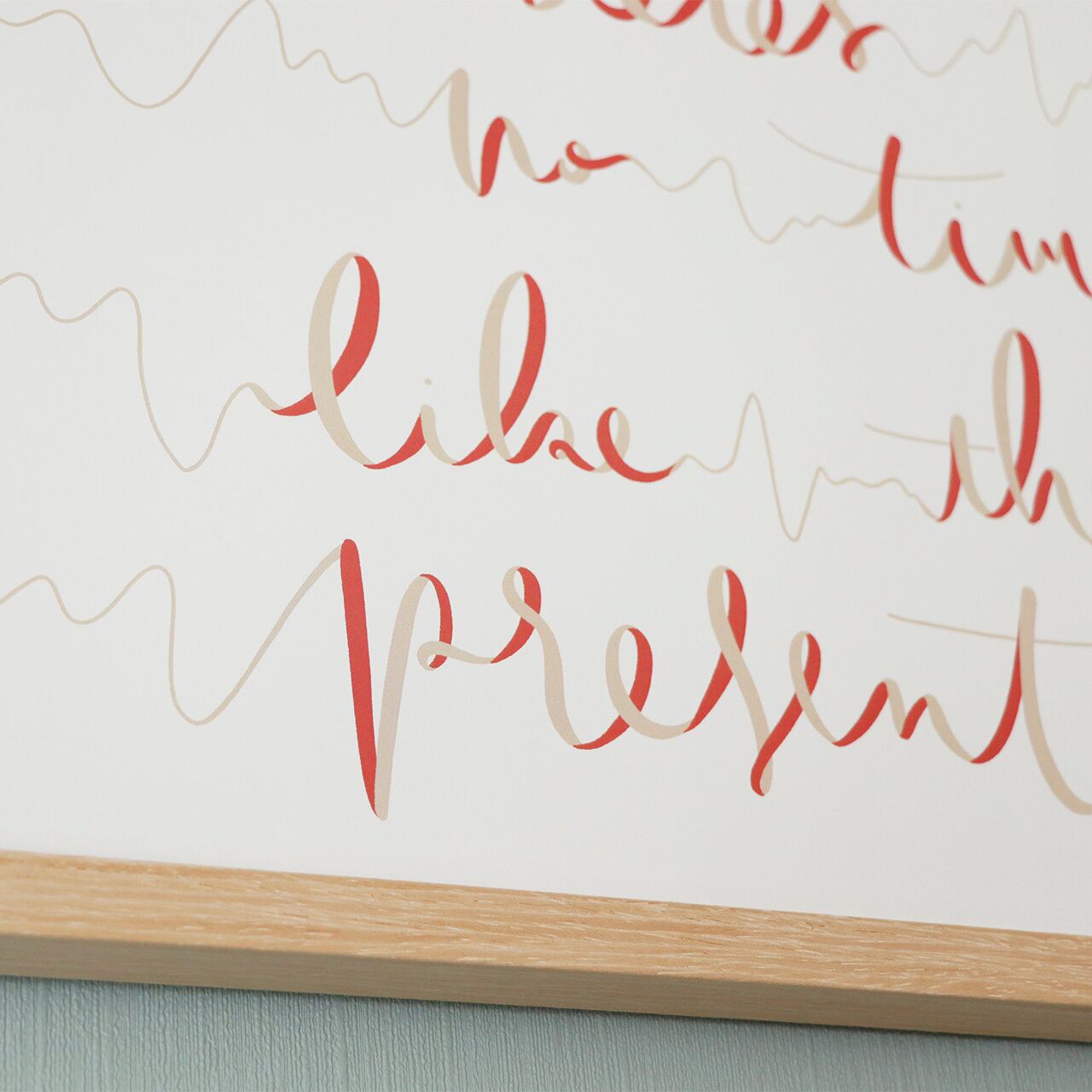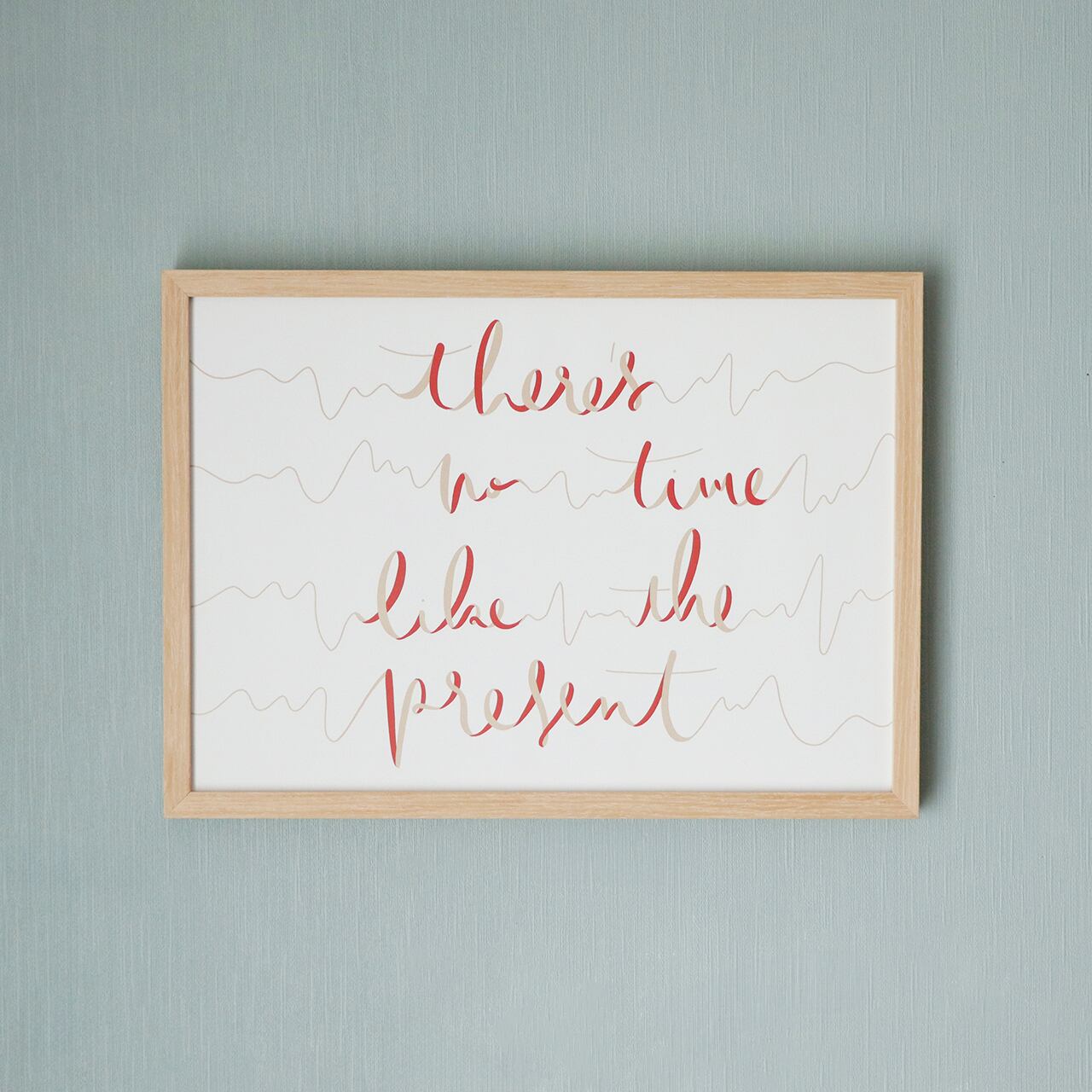
There's no time like the present (A3ポスター)
今回は2023年に描いた「There's no time like the present 」がもとになっています。
There's no time like the present /善は急げ
ドキドキして少し脈が上がってるのを、心電図の波形で表現しています。
なので通称「心電図」!!